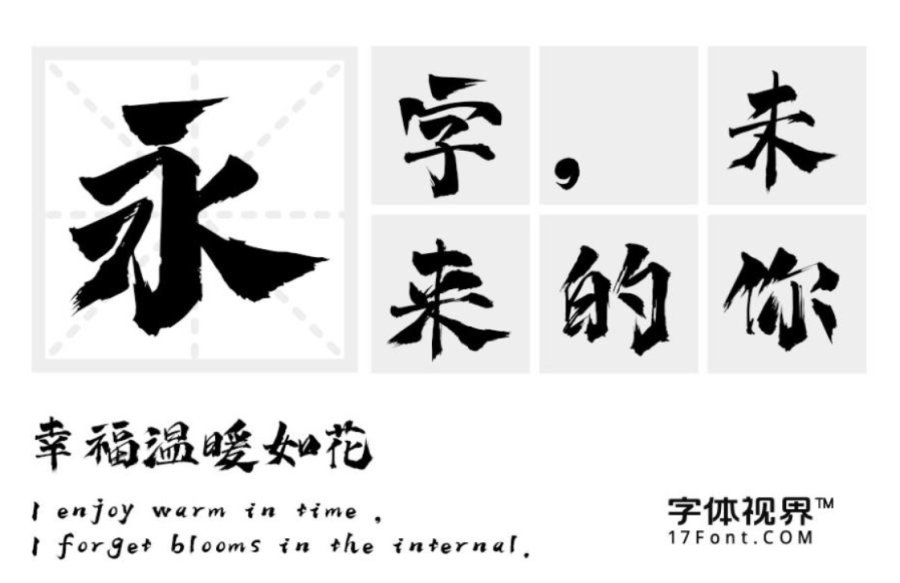
上首疾风书法体发布
字体名称:上首疾风书法体
字体类别: 书法字体
适用场景:标题、正文、印刷、屏显
上首疾风书法体简介:上首疾风体,字体风格锐利,钝点强力,夸张的笔锋增添了字体的活跃性,而且字体中粗细衔接,使字体显得生动。适用于包装和宣传设计及书法作品排版标题及正文、招牌设计等。
上首疾风书法体预览图展示: